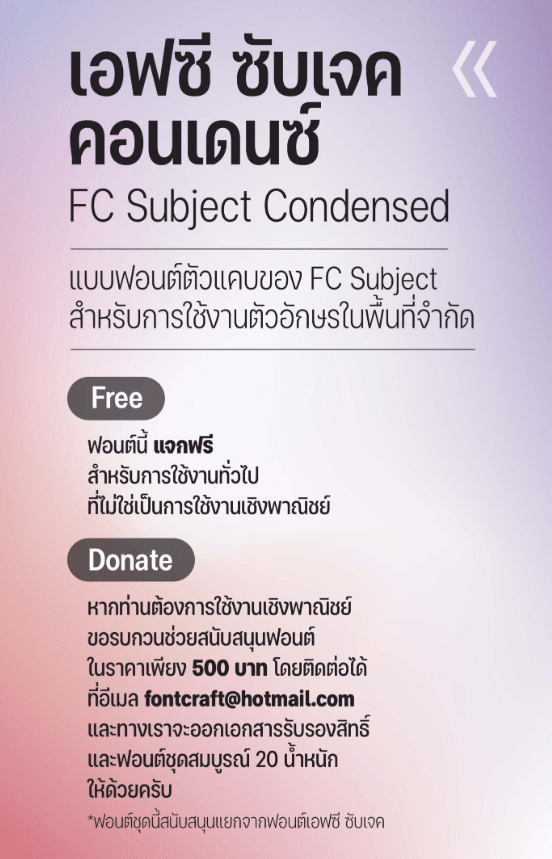
แบบฟอนต์ตัวแคบของ FC Subject สำหรับการใช้งานตัวอักษรในพื้นที่จำกัด
โดยสามารถลดพื้นที่ลงได้กว่า 18% โดยให้ผลลัพธ์ที่ดูสวยงามกว่าการบีบแคบแบบไม่ได้สัดส่วน
ฟอนต์เอฟซี ซับเจค คอนเดนซ์ มาพร้อมกับน้ำหนักถึง 10 ระดับ 20 สไตล์ และออกแบบมาให้สามารถเพิ่มช่องไฟตัวอักษรได้โดยสระและวรรณยุกต์ไม่เยื้องออกห่างจากแนวพยัญชนะ